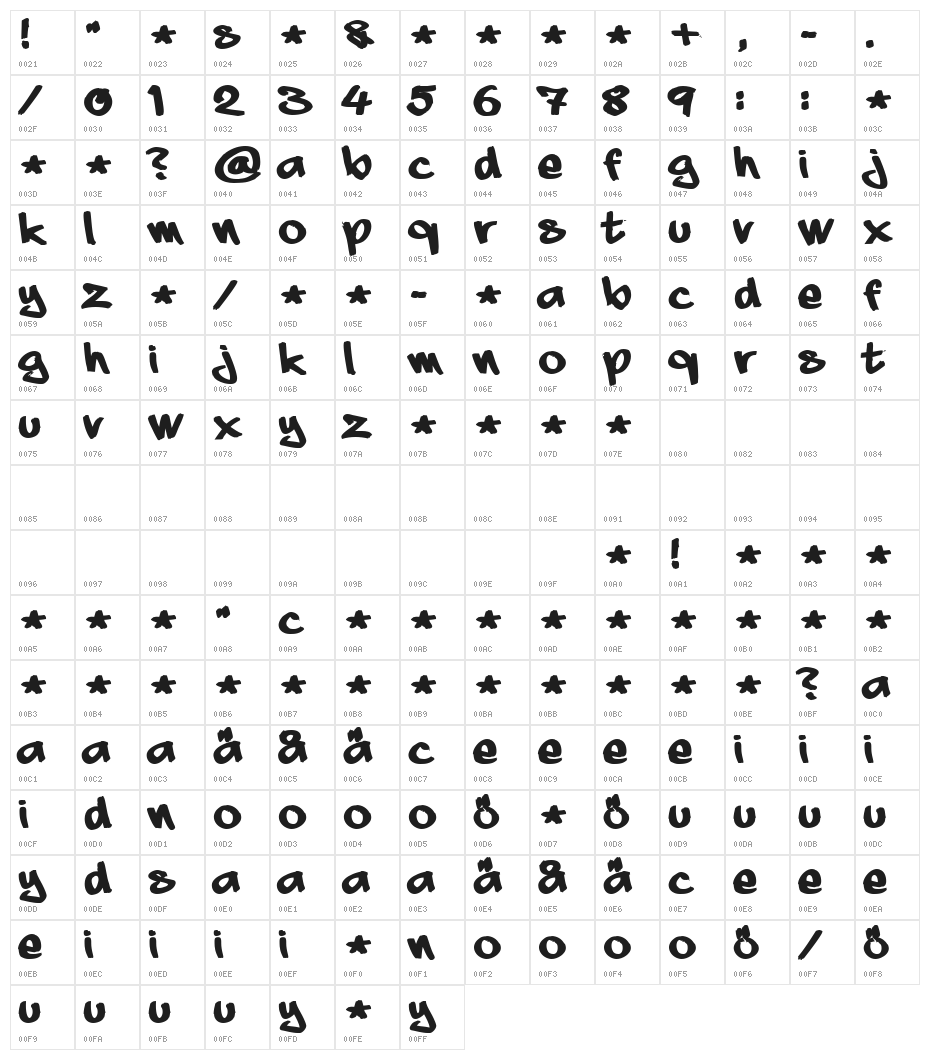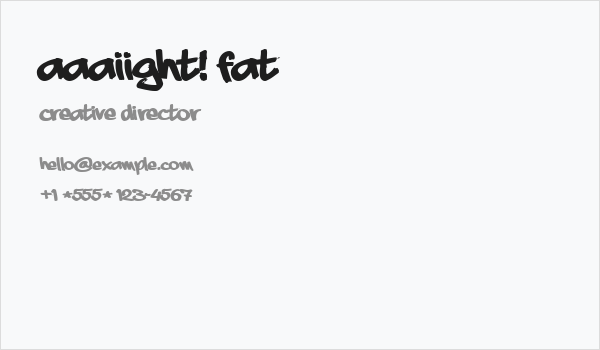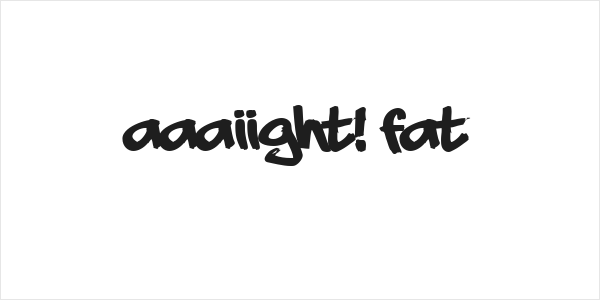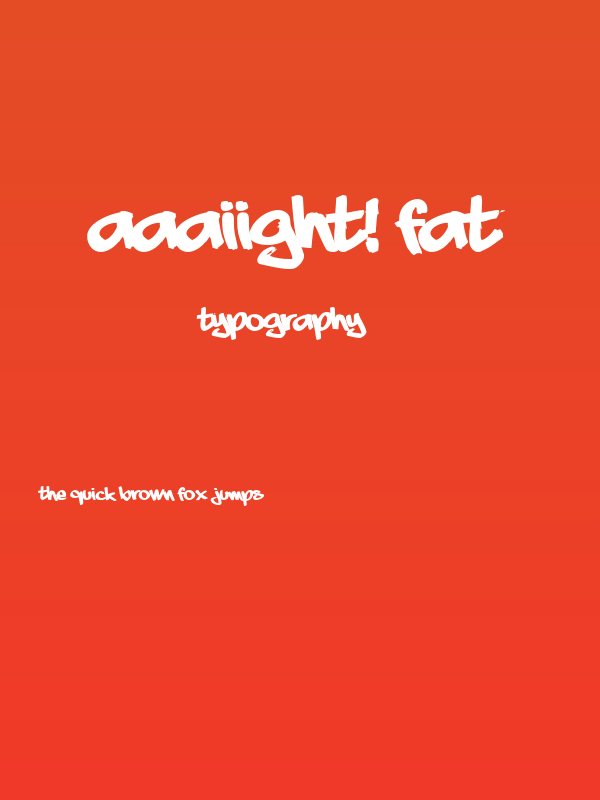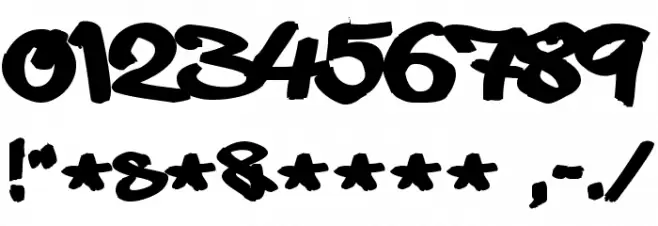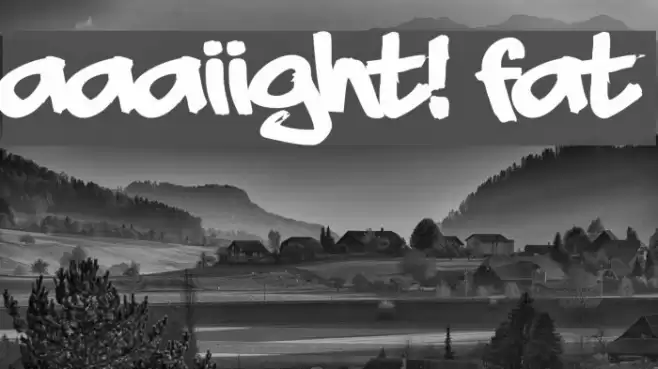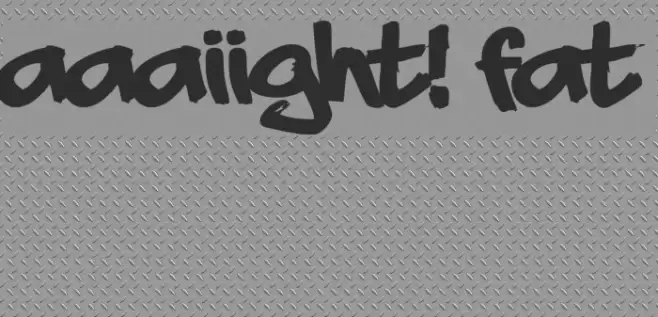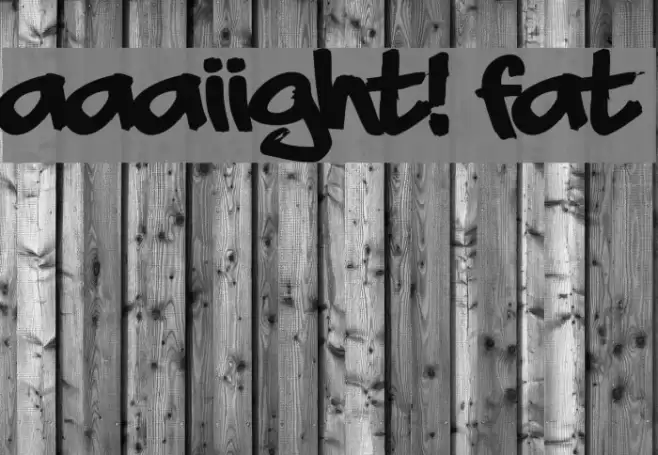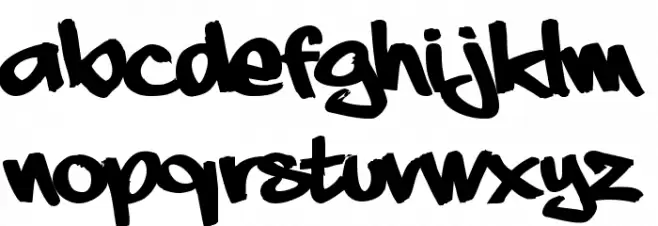
aaaiight! fat Font
| 全体的なスタイル | Urban, Graffiti, Energetic |
| 用途 | Logos, Posters, Headlines |
| おすすめプロジェクト | Ideal for street art designs, urban-themed posters, music album covers, and edgy branding projects. |